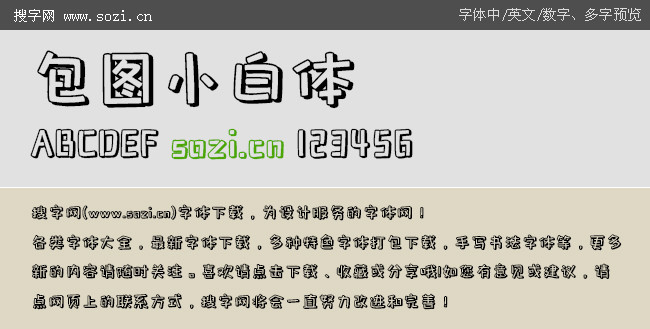
包圖小白體
搜字網(wǎng)給大家提供一款包圖小白體中文字體下載,包圖小白體是一款免費(fèi)的卡通字體,這款字體充滿童真,趣味性十足,適合應(yīng)用于藝術(shù)設(shè)計(jì)、兒童包裝設(shè)計(jì)、網(wǎng)頁設(shè)計(jì)、海報(bào)設(shè)計(jì)等應(yīng)用。